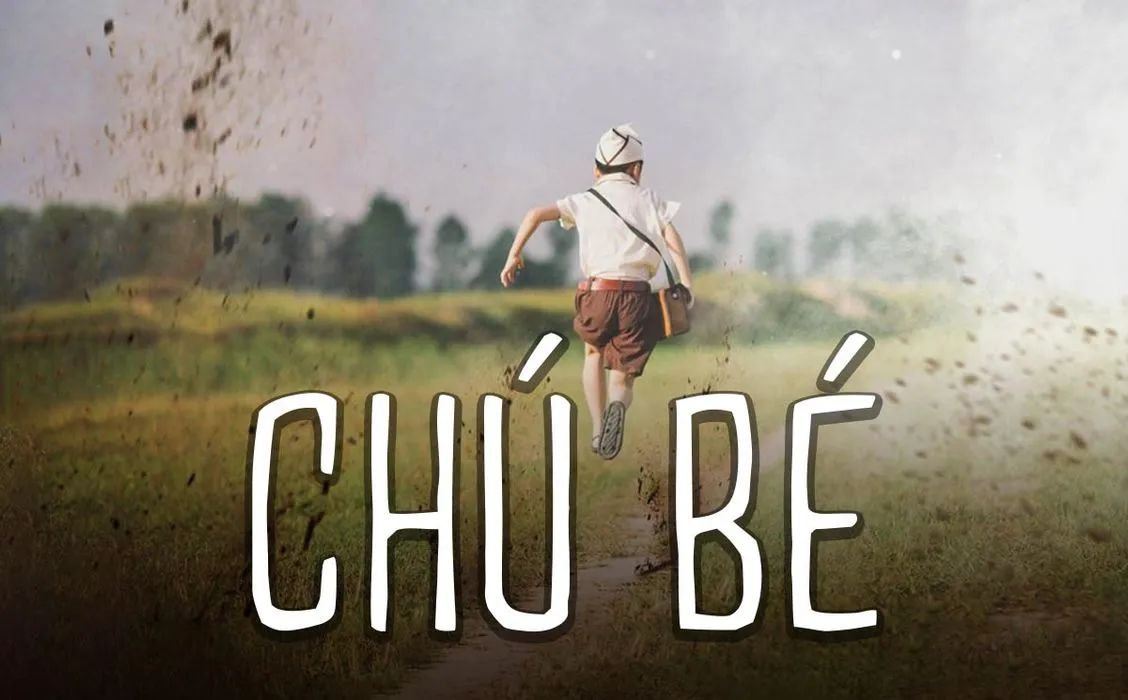
Nếu bạn đang tìm kiếm một bộ phông chữ vừa mang đường nét thanh lịch, hiện đại vừa đáp ứng hoàn hảo cho các thiết kế tiếng Việt, bộ Font iCiel Altus Việt Hóa chính là sự lựa chọn không thể bỏ qua. Được Việt hóa tỉ mỉ bởi iCiel, font chữ này mang lại trọn bộ ký tự tiếng Việt chuẩn chỉnh, hỗ trợ tối đa cho các nhà thiết kế đồ họa, sáng tạo nội dung và truyền thông thương hiệu. Hiện tại, trọn bộ 2 font chữ iCiel Altus độc đáo này đang được chia sẻ hoàn toàn miễn phí, sẵn sàng đồng hành cùng bạn trong mọi dự án thiết kế.
Trong thế giới thiết kế đồ họa đa dạng ngày nay, việc lựa chọn một font chữ phù hợp đóng vai trò quyết định đến 80% sự thành công của một sản phẩm truyền thông thị giác. Font chữ không chỉ truyền tải thông điệp bằng chữ viết mà còn thể hiện cảm xúc, cá tính và giá trị thương hiệu. Bộ Font iCiel Altus Việt Hóa ra đời như một giải pháp toàn diện cho những ai đang tìm kiếm sự cân bằng hoàn hảo giữa tính mỹ thuật cao và khả năng hiển thị rõ ràng.
Gần đây, cộng đồng designer Việt Nam đã dành rất nhiều sự quan tâm đến các bộ font Việt hóa từ iCiel nhờ chất lượng tác phẩm đạt chuẩn mực cao. Với phiên bản iCiel Altus, tác giả đã khéo léo tinh chỉnh hệ thống dấu tiếng Việt sao cho tự nhiên, cân đối nhất với cấu trúc nguyên bản của font gốc, loại bỏ hoàn toàn các lỗi dính dấu, lệch dấu hay vỡ nét thường gặp khi gõ tiếng Việt. Bộ tải về bao gồm 2 biến thể (2 styles) giúp bạn thỏa sức sáng tạo và phối hợp linh hoạt trong nhiều không gian nghệ thuật khác nhau.
1. Đường nét phong cách tinh tế, kết hợp hài hòa giữa hiện đại và cổ điển
Điểm ấn tượng đầu tiên của font iCiel Altus chính là cấu trúc hình học cân đối và nét chữ mang hơi hướng vừa hiện đại vừa ẩn chứa nét duyên dáng, cổ điển. Các góc bo và đường nét được gọt dũa tỉ mỉ, tạo ra sự thanh thoát nhưng vẫn giữ được sự chắc chắn, vững chãi cho từng ký tự. Bộ phông chữ này đặc biệt tạo ra hiệu ứng thị giác tuyệt vời khi được sử dụng ở kích thước lớn trong các tiêu đề (heading) hoặc câu khẩu hiệu (slogan).
Sự tinh tế của iCiel Altus giúp tác phẩm của bạn dễ dàng thu hút ánh nhìn của khách hàng ngay từ lần đầu tiên. Dù bạn sử dụng trên nền chất liệu in ấn hay màn hình kỹ thuật số, font chữ vẫn giữ nguyên được độ sắc nét và tính thẩm mỹ cao nhất.
2. Tối ưu hóa chuẩn Tiếng Việt với bộ dấu được tinh chỉnh hoàn hảo
Một trong những thách thức lớn nhất khi dùng các font chữ nước ngoài là dấu tiếng Việt thường bị thô, quá to hoặc làm đứt gãy bố cục chung của ký tự. Với phiên bản Font iCiel Altus Việt Hóa, mọi chi tiết về bộ dấu (sắc, huyền, hỏi, ngã, nặng, dấu mũ…) đều đã được tác giả iCiel nghiên cứu và căn chỉnh theo từng đường nét chữ.
Nhờ đó, khi soạn thảo văn bản tiếng Việt, các từ có chứa nhiều dấu phức tạp như “thưởng”, “nghiêng”, “chuỗi” vẫn hiển thị vô cùng thanh thoát, mượt mà và không hề gây cảm giác chật chội. Bộ font sử dụng bảng mã Unicode chuẩn, tương thích hoàn hảo với các bộ gõ phổ biến hiện nay như Unikey, Vietkey hay EVKey.
3. Trọn bộ 2 font chữ linh hoạt, đáp ứng đa dạng nhu cầu phối hợp bố cục
Gói tải về cung cấp trọn bộ 2 font chữ với độ đậm nhạt (weight) và phong cách được tùy biến linh hoạt. Sự kết hợp giữa 2 biến thể này cho phép các nhà thiết kế tạo ra sự tương phản thị giác rõ rệt (visual hierarchy) ngay trong cùng một tác phẩm mà không cần phải tìm kiếm thêm font chữ phụ trợ khác.
• Biến thể nét mảnh/thường (Regular/Light): Thích hợp cho các đoạn văn ngắn, lời dẫn, nội dung mô tả hoặc thiết kế mang phong cách nhẹ nhàng, tinh tế.
• Biến thể nét đậm (Bold/Medium): Hoàn hảo cho việc làm nổi bật tiêu đề chính, các con số ấn tượng, điểm nhấn trên banner truyền thông hoặc logo.
4. Ứng dụng phong phú trong nhiều lĩnh vực thiết kế truyền thông
Nhờ tính đa dụng và gu thẩm mỹ hiện đại, bộ font iCiel Altus Việt Hóa được ứng dụng rộng rãi trong hàng loạt các sản phẩm sáng tạo từ online đến offline:
• Thiết kế nhận diện thương hiệu: Sáng tạo logo, danh thiếp (business card), bộ nhận diện văn phòng, bao bì sản phẩm cao cấp.
• Truyền thông số (Digital Marketing): Banner quảng cáo Facebook, Google Ads, ảnh bìa fanpage, thumbnail Youtube, bài đăng Instagram.
• Ấn phẩm in ấn: Đồ họa bìa sách, tạp chí, poster sự kiện, tờ rơi, menu nhà hàng, thiệp mời cưới cao cấp.
• Nghệ thuật chữ (Typography): Sáng tạo các bức tranh chữ nghệ thuật, trích dẫn hay (quotes) chia sẻ trên mạng xã hội.
• Logo, bộ nhận diện thương hiệu của quán cà phê, tiệm bánh, cửa hàng thủ công mỹ nghệ.
• Poster, bìa sách, tạp chí phong cách retro.
• Bao bì sản phẩm, nhãn mác cần sự gần gũi và tự nhiên.
• Thiết kế typography nghệ thuật, trích dẫn trang trí.
Kết luận
Nếu bạn đang tìm kiếm một font chữ handmade độc đáo, vừa gần gũi vừa có cá tính mạnh mẽ, thì font iCiel Altus chính là lựa chọn lý tưởng. Với phiên bản Việt hóa hoàn chỉnh, bộ font này chắc chắn sẽ giúp các nhà thiết kế tại Việt Nam tạo nên những tác phẩm mang đậm dấu ấn cá nhân và phong cách vintage đầy cuốn hút.